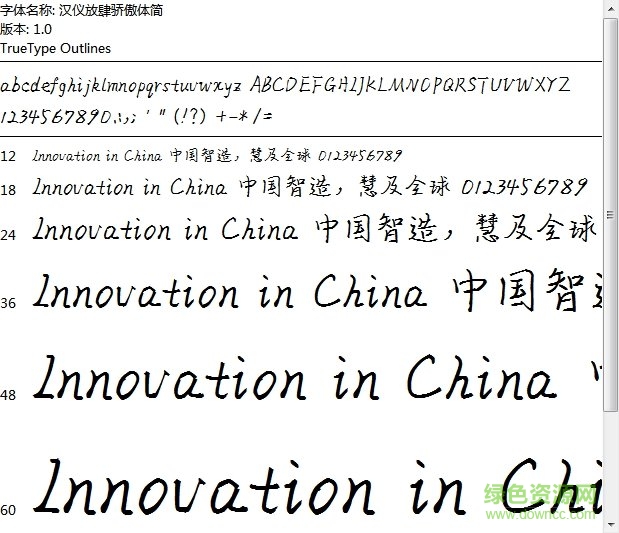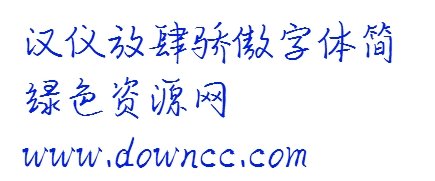
放肆驕傲字體ttf是一款源自于手機(jī)qq里的個性手寫字體,與漢儀晨妹子字體比較接近,字跡鋒利而不尖銳、穩(wěn)重而不失灑脫之風(fēng),喜歡的朋友就來綠色資源網(wǎng)下載吧!
不要太在乎一些人!
我依然可以驕傲放肆的笑!
追尋心中的信仰!
放肆驕傲體有著簡約流暢的筆觸,字跡雋永清秀、筆畫清晰大方,給人清爽的視覺呈現(xiàn),可以廣泛運(yùn)用于平面設(shè)計(jì)、logo設(shè)計(jì)、書信排版、海報(bào)設(shè)計(jì)等諸多場合!